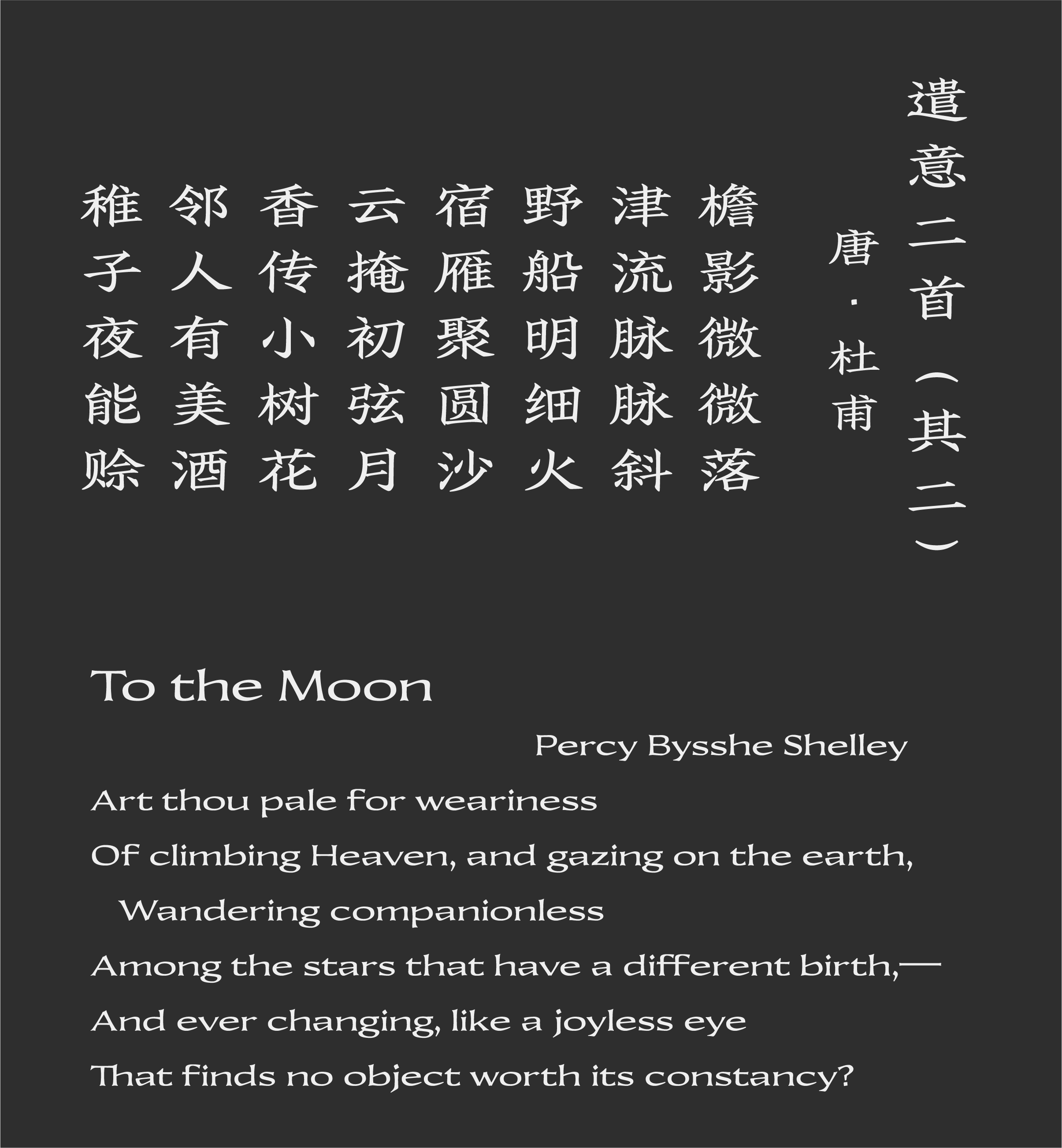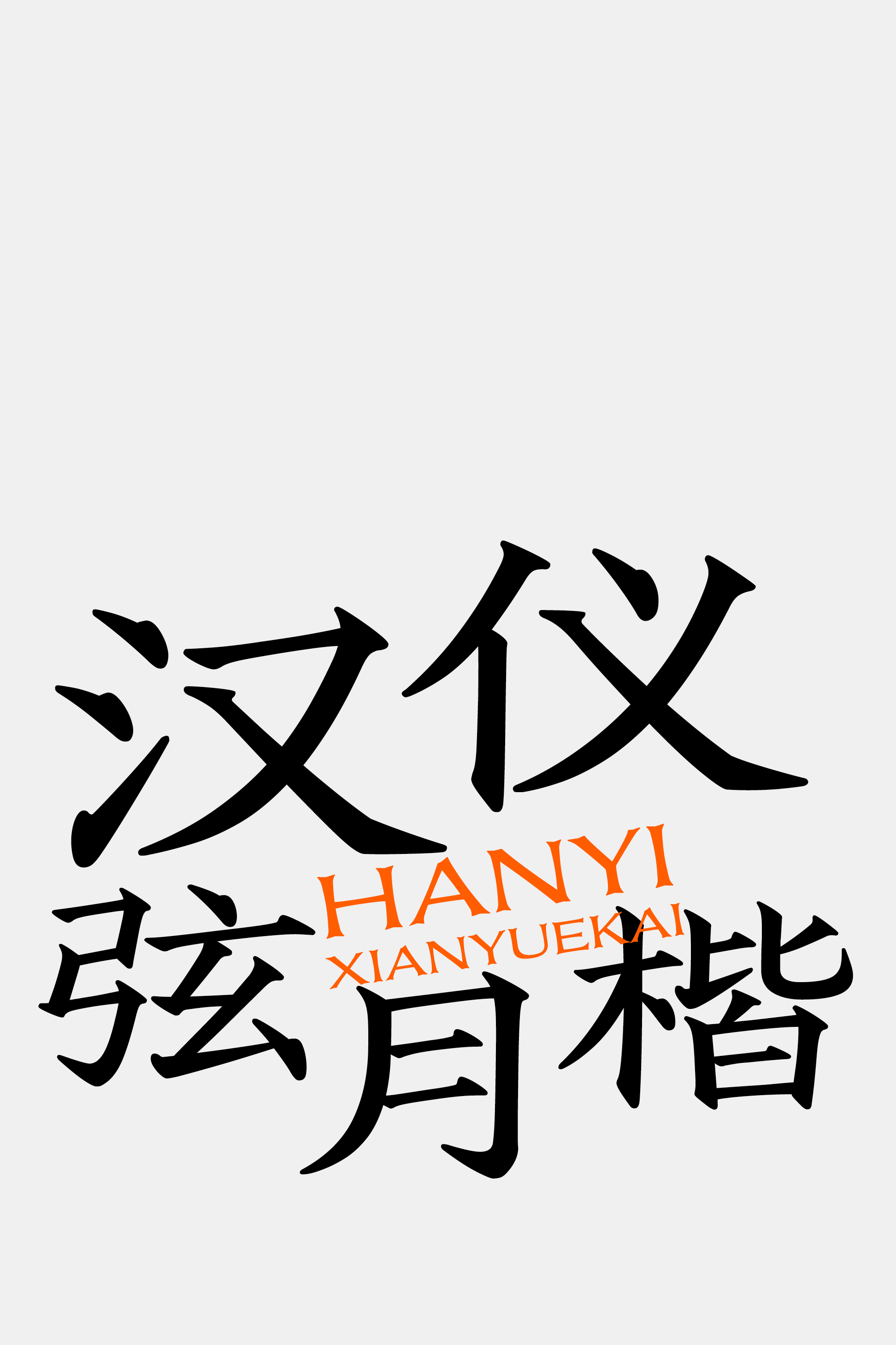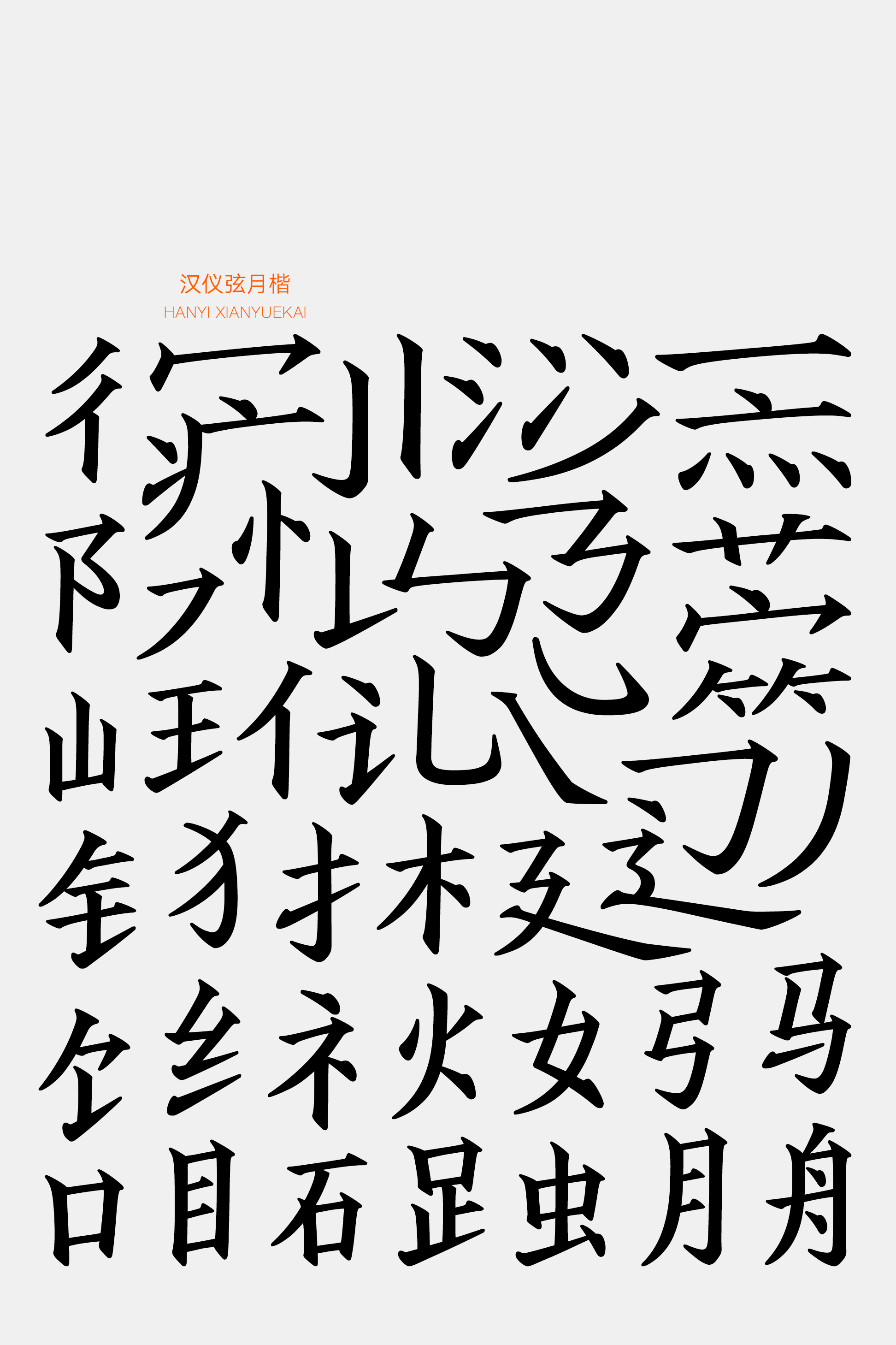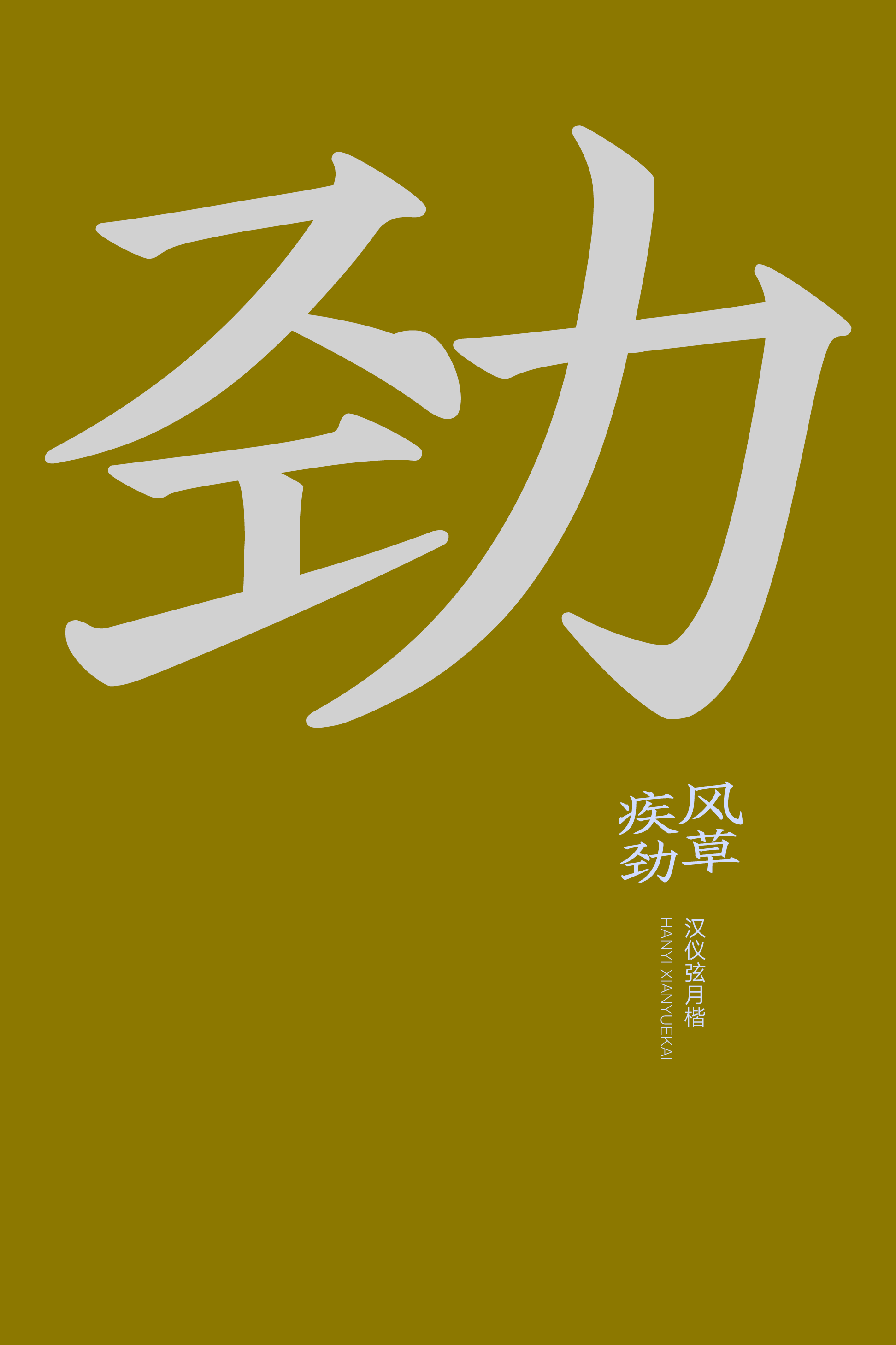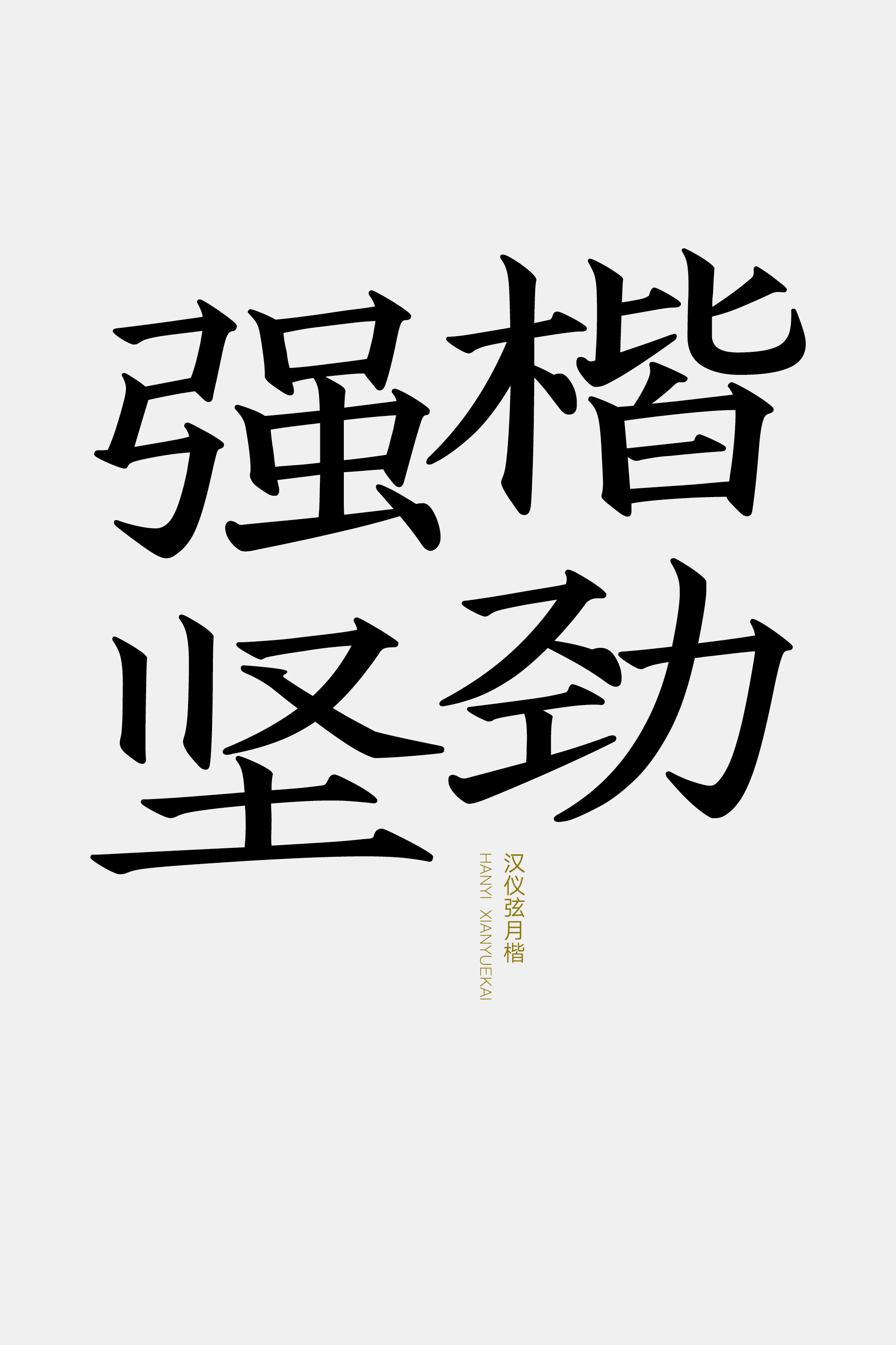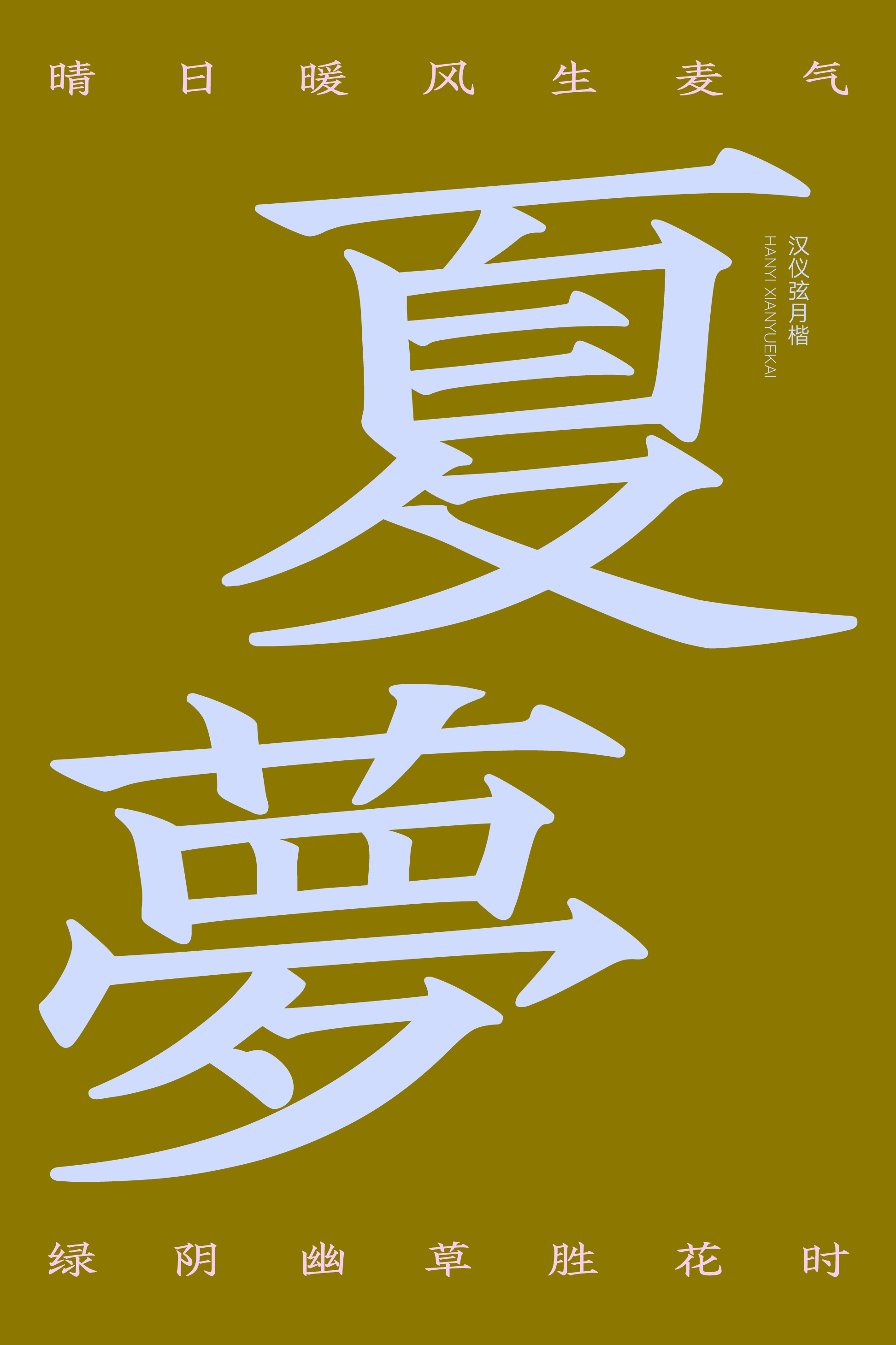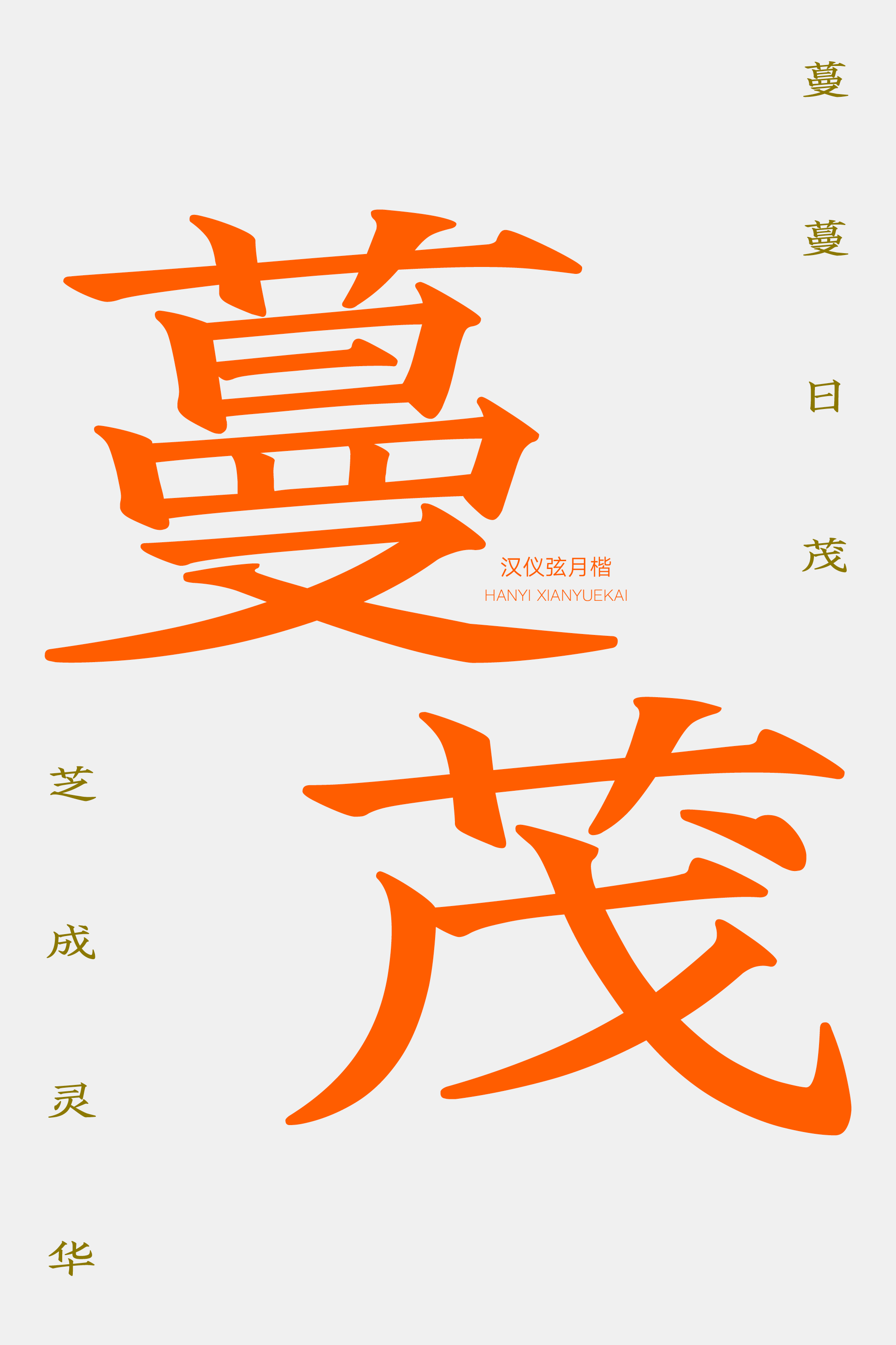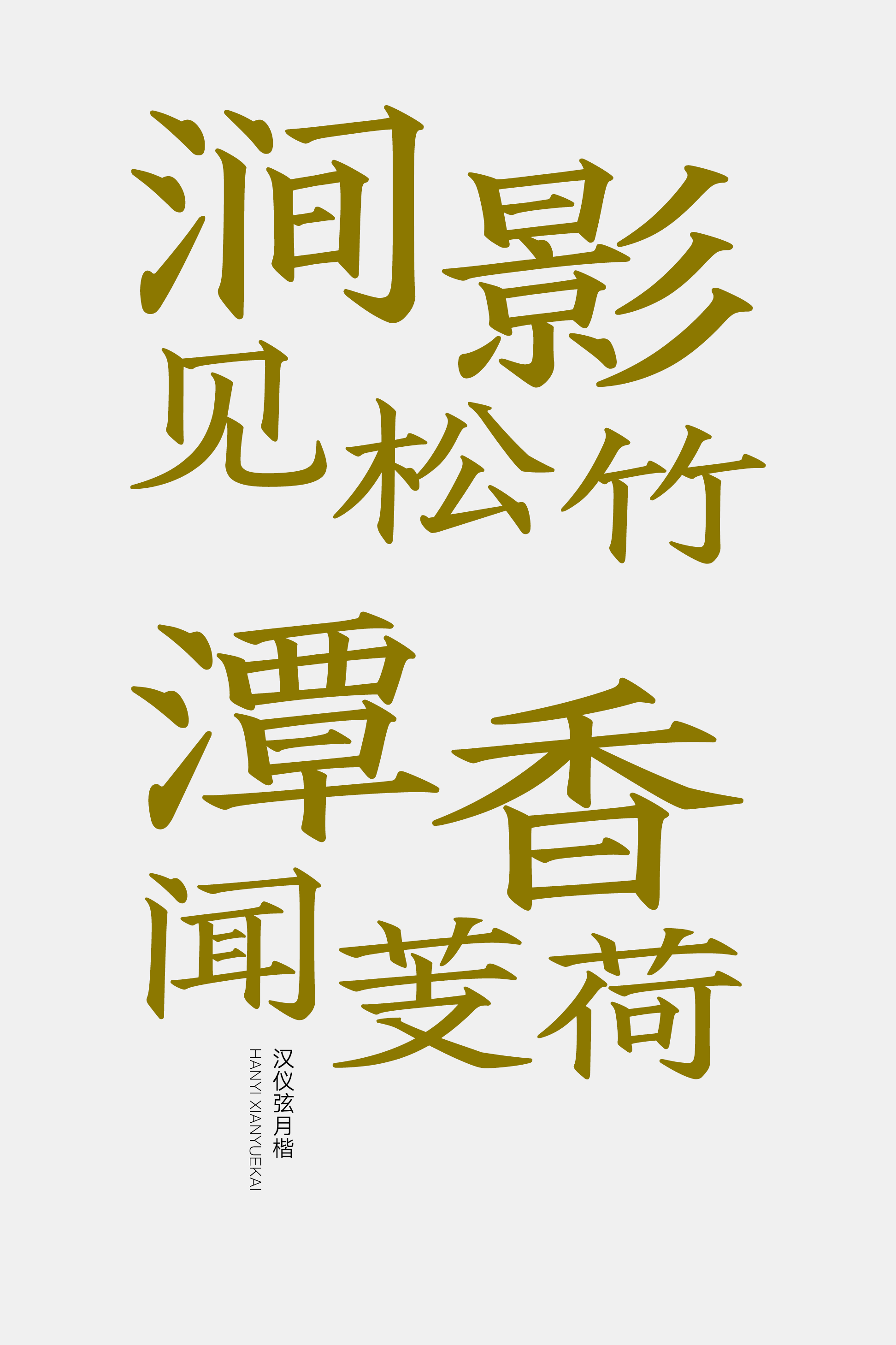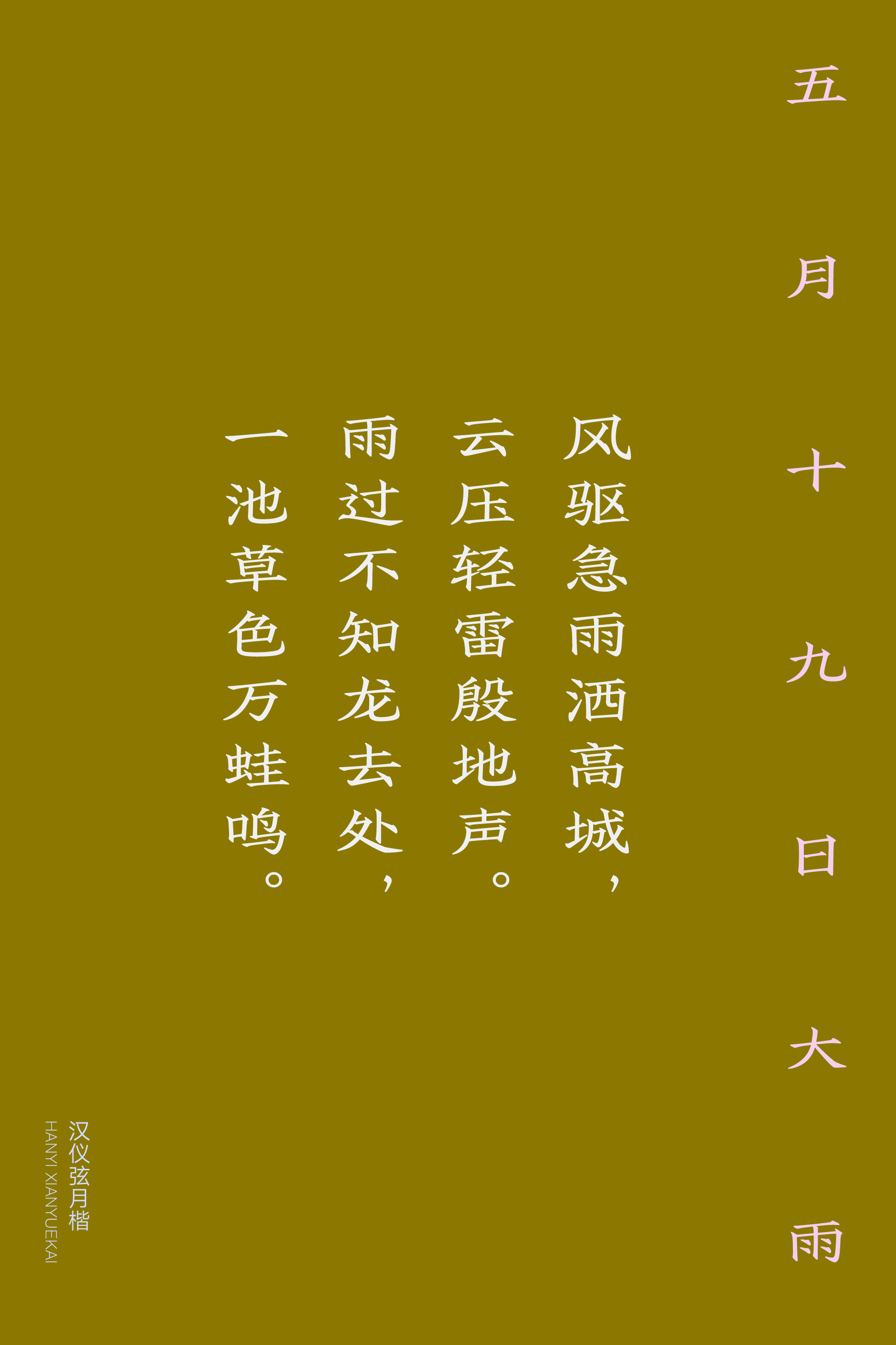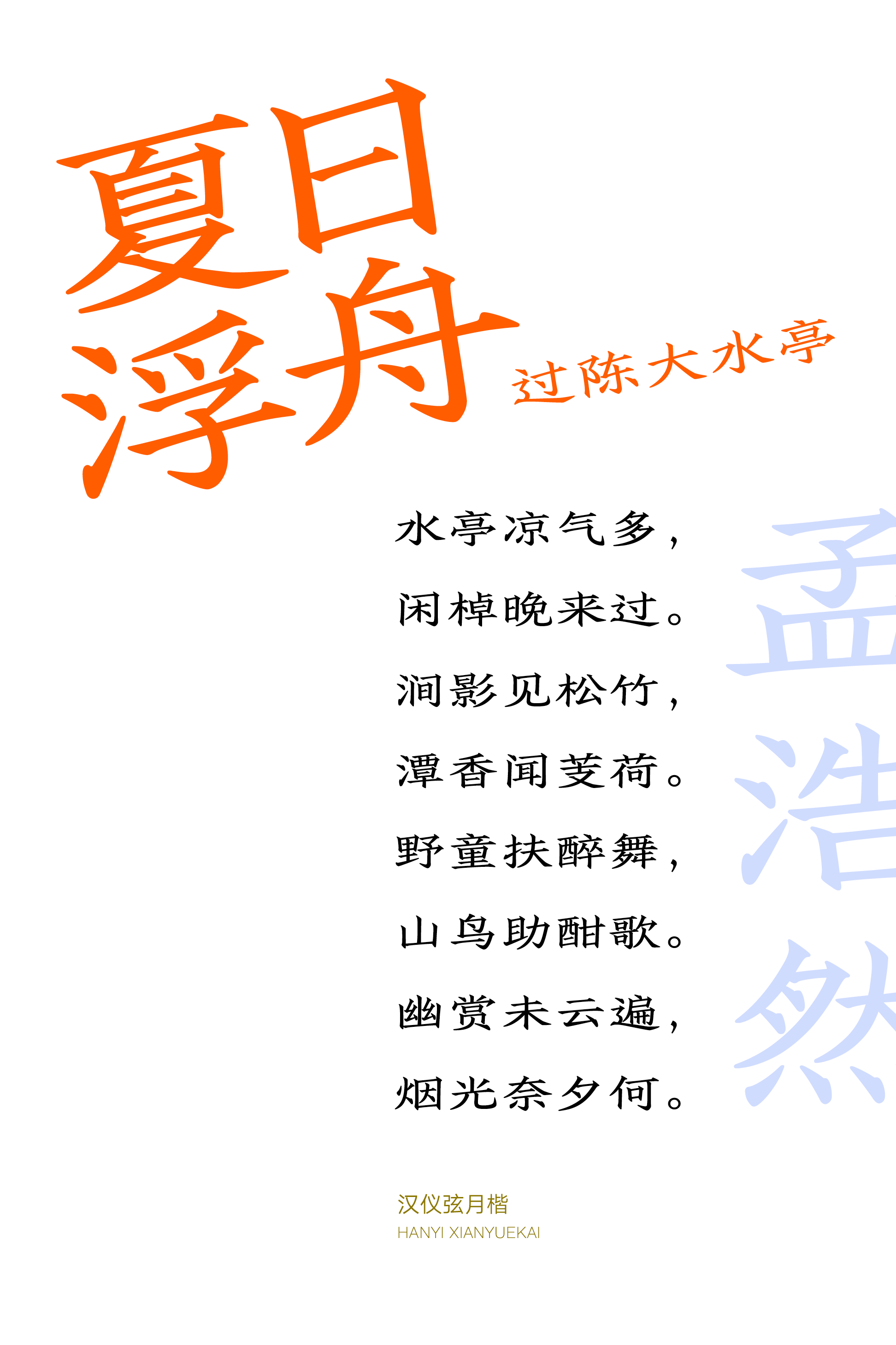
汉仪弦月楷
汉仪弦月楷,灵感源于三国时期钟繇所书《宣示表》,此帖处于隶楷错变的时代,书体蕴含着古雅的隶书意趣。宽扁通透的结构与温润平和的笔画细节赋予这款字体含蓄内敛、沉静优雅的气质,如弦月般清淡疏朗,流露古典气韵。汉仪弦月楷满足标题与正文的排版需求,适合于书籍封面、展览海报、品牌包装等多种使用场景。
汉仪弦月楷源自著名小楷法帖《宣示表》,原为三国时期钟繇所书,真迹已不可寻,刻本始见宋《淳化阁帖》。此帖处于隶楷错变的时代,楷书趋向成熟,捺脚保留有浓重隶书波磔意趣,极为古雅。
字形扁方而结构通透。
重心偏低,中宫放松,略带斜势。
笔画柔韧,起收笔作温润平和的处理。
汉仪弦月楷的西文部分由汉仪字库西文字体设计师史贺达创作,基于古典风格,加入了一些源于西文书法笔意的视觉元素,沉稳的造型与张扬的细节相互平衡,贴合中文温润优雅的气质。
整体造型与传统罗马体(Roman)相比更为宽扁。
作较为张扬的细节设计:曲线圆中有方,字腔形状转折强烈;点状作菱形设计。这些看似张扬的视觉元素源于对西文书法和文字绘写(Lettering)笔意的提取和应用。
除了字母造型,对于匹配书写所带来的视觉感受有着诸多考量:选择了衬线较为短小的设计,衬线中央作形似喇叭口的凹陷处理,巧妙地保留了西文手写韵味;字干中部微微收张的趋势也与中文竖画形成呼应。
汉仪弦月楷,中文和西文都源于古典语言而进行了现代化设计,千年以前的弦月沉静温和地落在今日的字里行间,细腻入微、古意悠扬,形成独特的排版节奏。